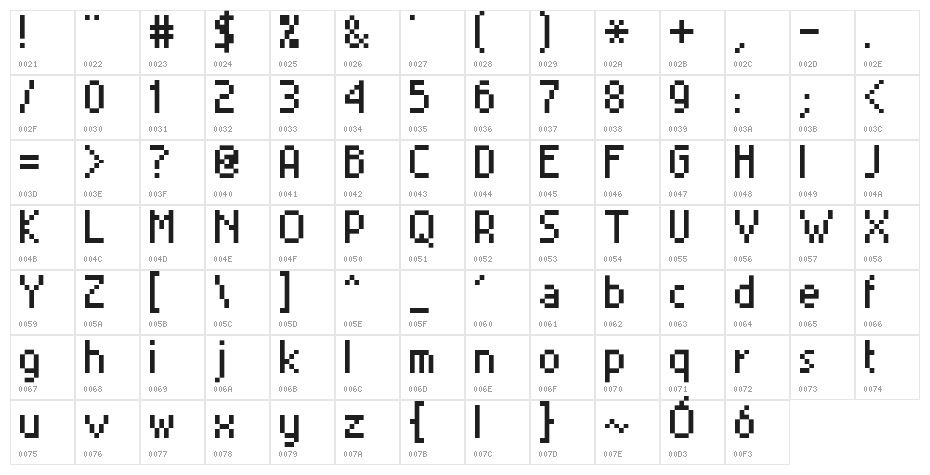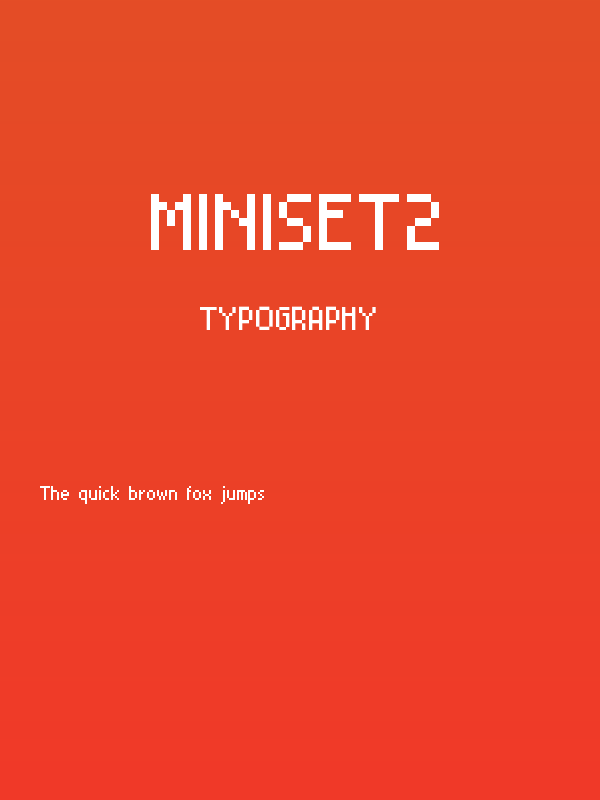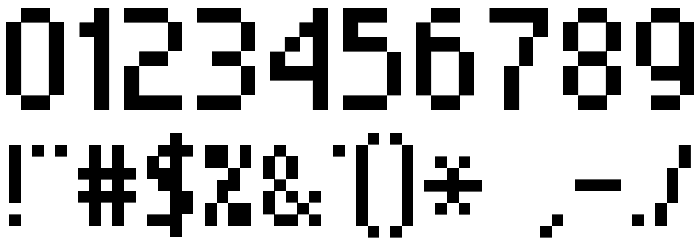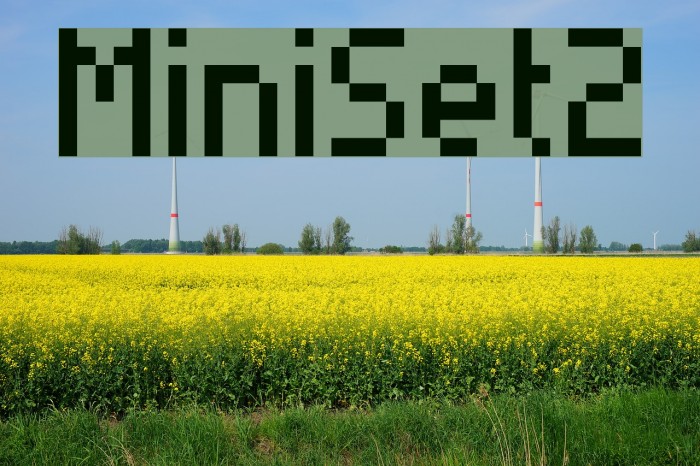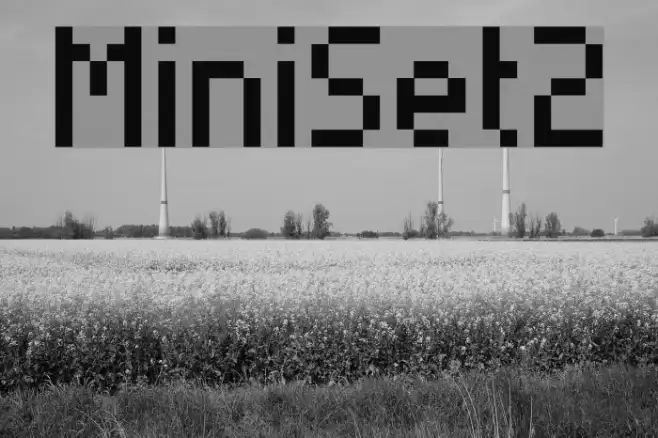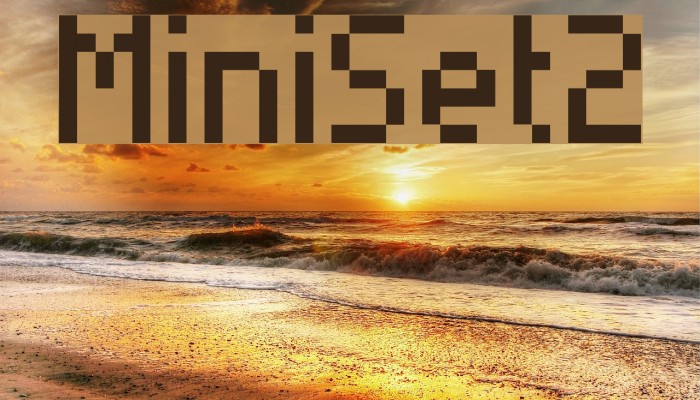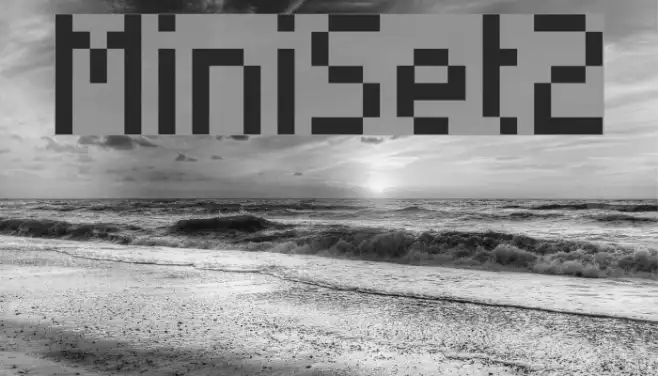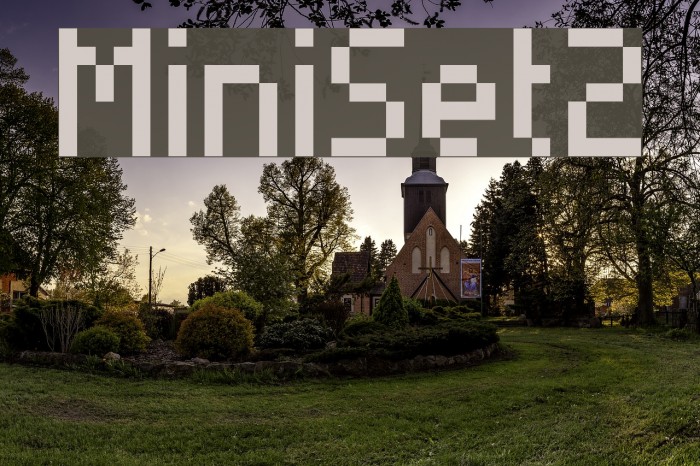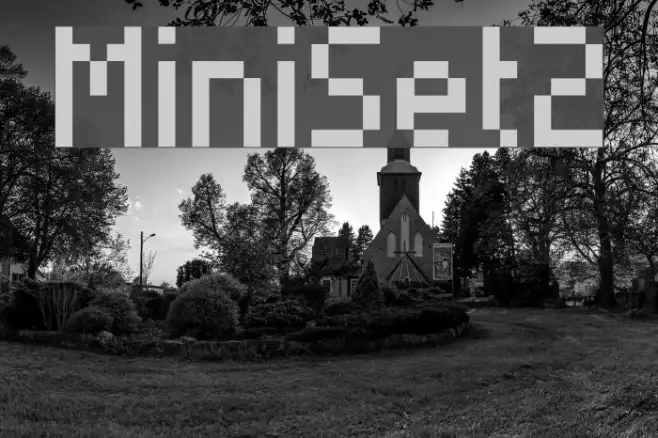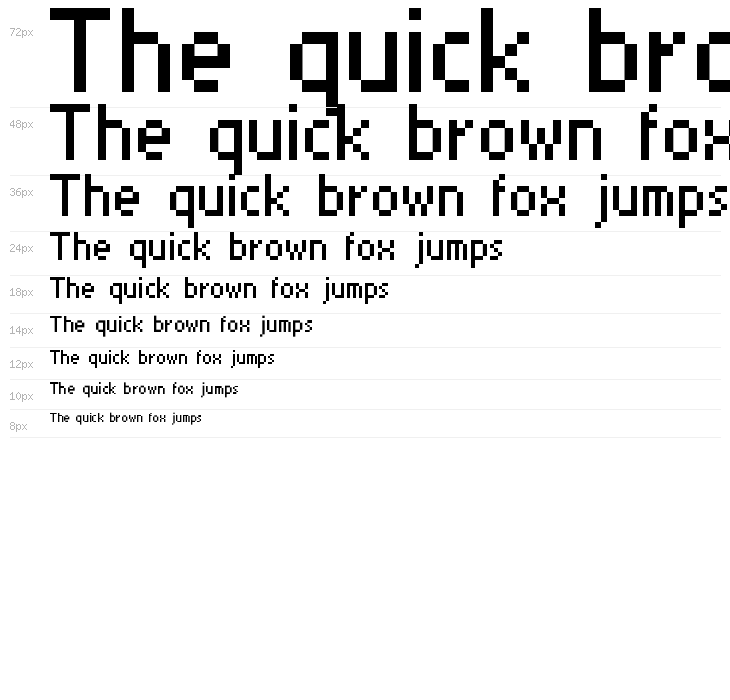
MiniSet2 Font
✎ Pixel
| Style général | Retro |
| Cas d'utilisation | Logos, Headlines, Digital Art |
| Projets proposés | Ideal for retro video game designs, digital art projects, tech-themed posters, and any creative work that seeks to capture a vintage digital aesthetic. |